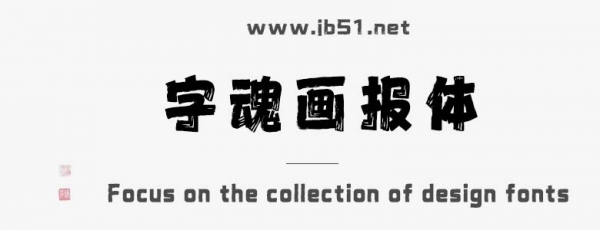
字魂畫報體由字魂字庫推出的藝術(shù)字體,該該字體包含9503個中文、字母、 符號和數(shù)字,具有輕松休閑的風(fēng)格,適合應(yīng)用于藝術(shù)設(shè)計、平面宣傳設(shè)計、網(wǎng)頁設(shè)計,書法字帖等領(lǐng)域。
字魂畫報體字體是一款商用的創(chuàng)意,卡通可愛,創(chuàng)意書寫,創(chuàng)意標(biāo)題字字體,該字體包含9503個中文、字母、 符號和數(shù)字,具有輕松休閑的風(fēng)格,可以滿足您設(shè)計上的各種需求,該字體主要用于廣告宣傳等場景, 您不但可以在字魂網(wǎng)下載字魂畫報體字體,同時還有眾多毛筆書法字體、創(chuàng)意字體等可供選擇!